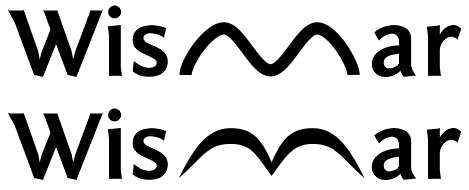
Schriftart gesucht bei dem "m" eine Art Welle oder Möwe ist
Hallo, ich suche eine Schriftart, in der das "m" langgezogen ist und ähnlich ist wie eine Welle oder Möwe. Das "m" sollte also geschwungen sein.
Wer kennt eine solche Schrift?
Ja, wie bei dem dem ersten Wort Wismar, sollte die Welle in etwa sein. Die nachfolgenden Buchstaben der Schrift natürlich dann dementsprechend.